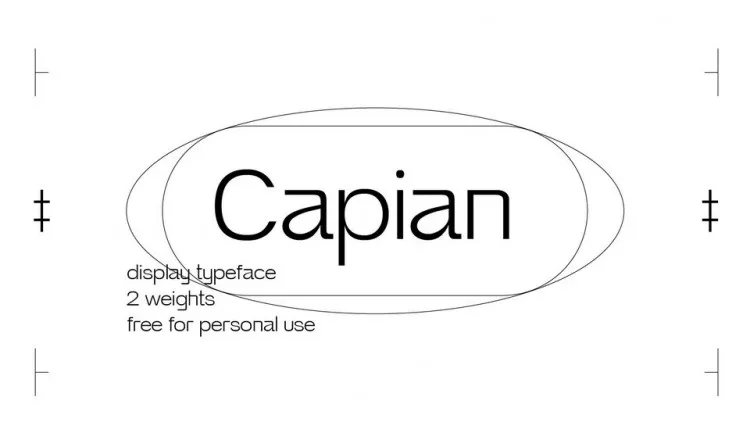
A fonte Capian é uma escolha perfeita para designers que buscam tanto elegância quanto simplicidade no seu trabalho. Desenvolvida pelo designer Dániel Domonkos, a Capian é uma sans-serif rica e elegante, adequada tanto para tipografias visuais chamativas quanto para fontes limpas e leíveis para texto menor. Com dois pesos disponíveis – Regular e Bold –, ela oferece flexibilidade que permite adaptar a aparência da fonte de acordo com o projeto. Capian é uma excelente opção para qualquer designer que procura uma tipografia moderna e versátil, perfeitamente adequada tanto para aplicações digitais quanto impressas.